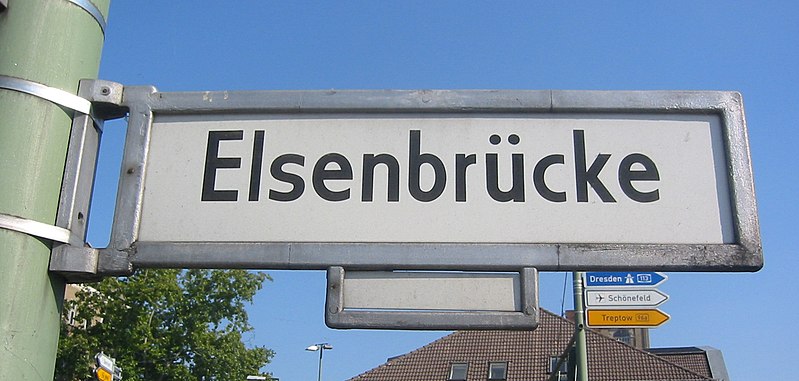
Suche Berliner Straßenschild Font um 1920!!!!!!
ich suche dringend den Schrifttyp um 1920 der für die Berliner
Straßenschilder verwendet wurde. Wer hat da ne Ahnung oder weiß genaueres?
Ach ja, ne Abbildung finde ich nicht im Internet (vom Straßenschild um 1920)
Ist bei diesen hier das dabei, was Du suchst?
Die Beiden oberen West-Nachkriegs-Modell (CST Berlin West)
keine Ahnung, kann man »historisches« Emailleschild kaufen.
Nachkriegs-Ost-Modell.
Die Schilder in der Schriftart »FF CST Berlin West« sind aber nicht typisch Berlin spezifisch. Die Bundesstadt Bonn verwendet ebenfalls diese Straßenschilder.